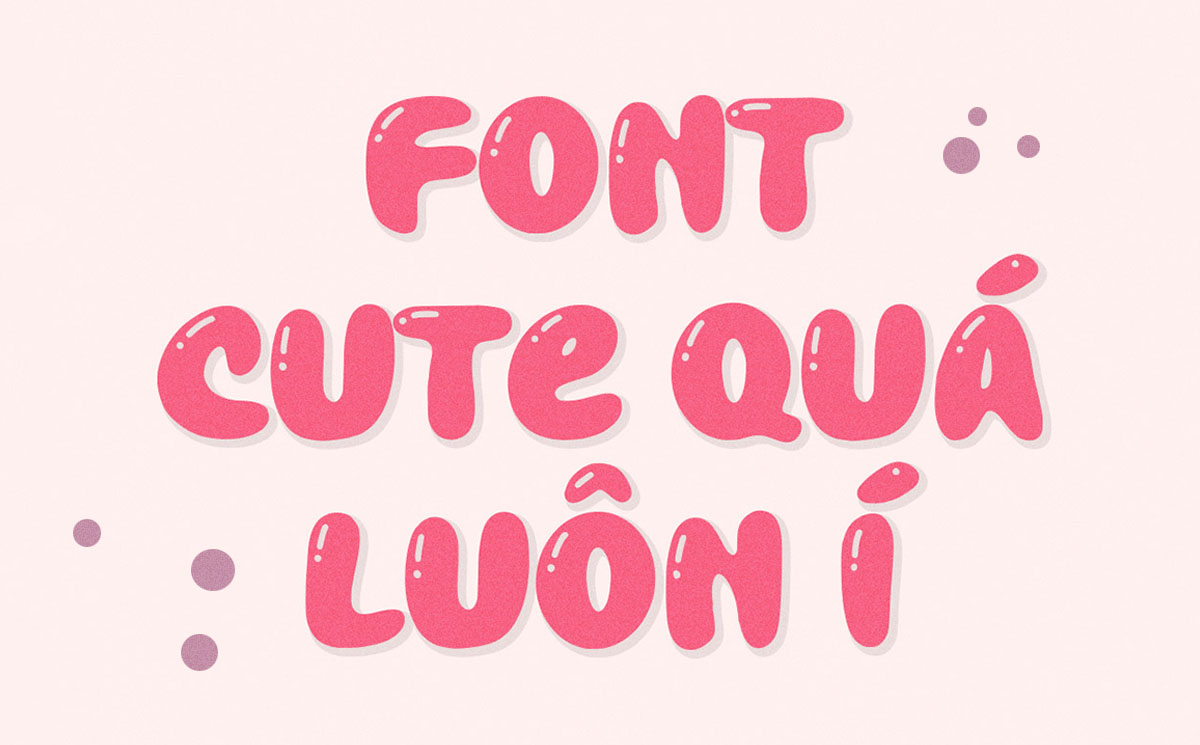
SVN Bublont là bộ phông chữ thuộc dòng Bubble Display mang phong cách bong bóng phúng phính, ngọt ngào và tràn đầy năng lượng tươi vui. Với cấu trúc nét chữ dày mập, các góc cạnh được bo tròn tròn trĩnh như những quả bóng bay phồng căng, phông chữ này là lựa chọn số một cho các thiết kế bao bì bánh kẹo, nhãn dán trà sữa, sản phẩm thiếu nhi và các chiến dịch quảng cáo trẻ trung. Doozypack.vn cung cấp link tải font SVN Bublont Việt hóa chuẩn kỹ thuật, giúp bạn sở hữu phông chữ đáng yêu này mà không lo gặp bất kỳ lỗi hiển thị dấu thanh nào khi thiết kế in ấn.
Đặc điểm thẩm mỹ độc đáo của bộ font SVN Bublont
Bublont không đi theo sự nghiêm nghị của các phông chữ hình học truyền thống; nó mở ra một không gian đồ họa đầy ắp niềm vui, mang lại cảm giác hào hứng và ngọt ngào cho người xem.
Phong cách Bubble Display phúng phính và ngập tràn niềm vui
Đặc trưng lớn nhất của SVN Bublont là hình khối chữ cái căng tròn như những viên kẹo ngọt hoặc bong bóng xà phòng rực rỡ. Cấu trúc chữ có độ dày nét (weight) cực lớn cùng những mảng mực đặc đầy đặn, tạo ra một sức hút thị giác vượt trội. Khi đặt Bublont làm tiêu đề trên bao bì, tên sản phẩm của bạn sẽ ngay lập tức trở thành tâm điểm của sự chú ý, tạo cảm giác thân thiện và kích thích vị giác của khách hàng ngay từ cái nhìn đầu tiên.
Cấu trúc chữ bo tròn tuyệt đối tạo cảm giác thân thiện
Tất cả các điểm kết thúc và góc nối của SVN Bublont Việt hóa đều được xử lý bo cong mượt mà, loại bỏ hoàn toàn cảm giác sắc nhọn cứng nhắc. Thiết kế này mang lại tâm lý an tâm, gần gũi và ấm áp, cực kỳ ăn ý với các thương hiệu dành cho mẹ và bé, đồ chơi sáng tạo hoặc các dòng sản phẩm đồ ăn vặt hướng tới học sinh, sinh viên.
Ưu điểm nổi bật của bản SVN Bublont Việt hóa
Khi ứng dụng các phông chữ nét béo mập vào thị trường trong nước, sự chỉn chu về dấu câu là yếu tố quyết định đến tính thẩm mỹ của ấn phẩm:
- Khắc phục triệt để lỗi dấu tiếng Việt: Phiên bản Việt hóa của SVN Bublont đã được đội ngũ thiết kế trau chuốt thủ công từng dấu câu. Các dấu sắc, huyền, hỏi, ngã, nặng được vẽ căng mọng, bo tròn đồng điệu với thân chữ gốc, không gây cảm giác chắp vá hay làm biến dạng cấu trúc chữ.
Lời khuyên từ xưởng in: Vì Bublont là phông chữ có nét chữ rất dày và các khe hở trong chữ khá nhỏ, khi bạn thiết kế in ấn trên chất liệu giấy Kraft hoặc giấy có bề mặt nhám thô, hãy ưu tiên sử dụng định dạng OTF và tăng nhẹ khoảng cách giữa các chữ cái (Tracking) để tránh hiện tượng mực bị lan làm bít các khe chữ nhỏ như chữ ‘e’ hay ‘a’.
03 Ứng dụng thực tế của font SVN Bublont trong sản xuất bao bì
Sự ngọt ngào và năng động của Bublont mang lại hiệu ứng thị giác đắt giá trên các dòng sản phẩm bao bì thực tế do Doozypack.vn sản xuất:
- Hộp giấy bánh kẹo & Đồ ăn vặt (Snacks): Nét chữ bong bóng gợi cảm giác ngon miệng, rất hợp làm tiêu đề chính trên hộp bánh cookie, túi kẹo dẻo hoặc hộp bỏng ngô rạp chiếu phim.
- Tem nhãn dán Trà sữa & Nước trái cây: Dùng cho tên thương hiệu in trên tem decal trong hoặc tem niêm phong ly nước mang phong cách dễ thương, tươi mới.
- Bao bì sản phẩm thiếu nhi & Đồ chơi: Tiêu đề in bằng font Bublont trên nền hộp giấy rực rỡ tạo sự hào hứng và thu hút sự chú ý của các bạn nhỏ ngay tức thì.
Lưu ý kỹ thuật khi in ấn với phông chữ béo bong bóng Bublont
- Kiểm soát hiện tượng tràn mực (Dot Gain) tại khe chữ nhỏ: Các khoảng hở bên trong chữ cái của Bublont khá hẹp. Khi in trên giấy có độ thấm mực cao, mực có thể bị lan làm bít kín các lỗ hở này. Bạn nên giữ size chữ tiêu đề tối thiểu từ 10pt trở lên để đảm bảo độ sắc nét.
- Lựa chọn hệ màu rực rỡ: Phong cách Bublont đẹp nhất khi phối với các tông màu tươi sáng hoặc màu Pastel ngọt ngào. Một đường viền (Stroke) mỏng quanh chữ cũng giúp tiêu đề trông “nổi” và sắc nét hơn trên vỏ hộp.